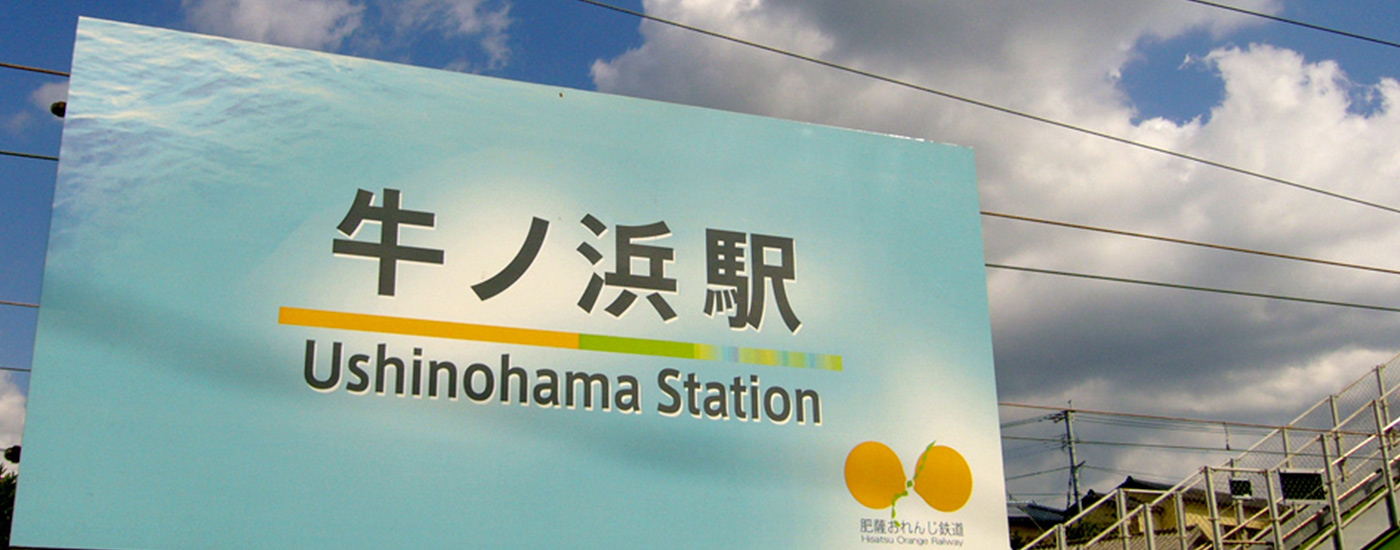
駅という「公共空間」で機能する書体
建築家 川西 康之氏
デンマーク王立芸術アカデミー都市デザイン科招待生として渡欧後、オランダDRFTWD officeやフランス国鉄交通拠点整備研究所(AREP-SNCF)都市設計部などで活躍した建築家の川西康之氏が、2004年に手がけたのは肥薩おれんじ鉄道(八代駅〜川内駅)のロゴタイプとサイン計画でした。
JR鹿児島本線の一部であった熊本県八代と鹿児島県川内を結ぶ路線が第三セクター方式で再出発することになりました。肥薩おれんじ鉄道というみずみずしい名称には、旧国名の「肥後」と「薩摩」の頭文字に加え、沿線で栽培されている柑橘類のイメージが盛り込まれています。川西氏は、精度の高い文字と路線にふさわしいデザインを導入することで、駅という空間や鉄道で移動するという体験に新しい視点を盛り込みたいという思いからロゴタイプだけでなく、統一的なサイン計画を提案しました。
そのために川西氏が選んだのはAXIS Fontでした。風光明媚な自然に囲まれた空間であり、かつミニマムな要素のみで構成された駅舎にはシンプルであたたかみのある書体がふさわしいと直感したのだそうです。
「利用者のためにできることを考えたときに凛として白に映えるAXIS Fontしか考えませんでした。書体としての完成度だけでなく、日本語と英語を併記した時のバランスの良さは抜群ですね。駅名を漢字・ひらがな・アルファベットで同じスペースに配置しても違和感が無い。私は建築家であり、グラフィックデザインを専門的に学んできたわけではないにもかかわらず、完成度の高い文字組を実現できたのはAXIS Fontのおかげだと思っています」
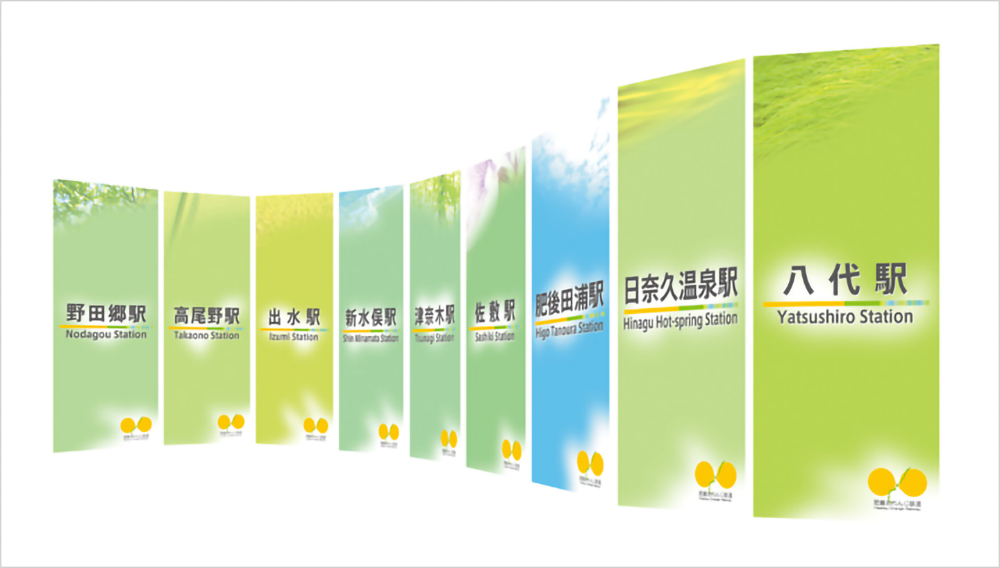
川西氏は土佐くろしお鉄道の主要駅のひとつである中村駅のリノベーションも手がけました。こちらも第三セクター方式を導入し1988年に誕生した路線です。当初はJR中村線を引き継ぐかたちで運行していましたが宿毛線やごめん・なはり線も加わり、現在では高知県の基幹をなす公共交通機関として地域住民や観光客に親しまれています。
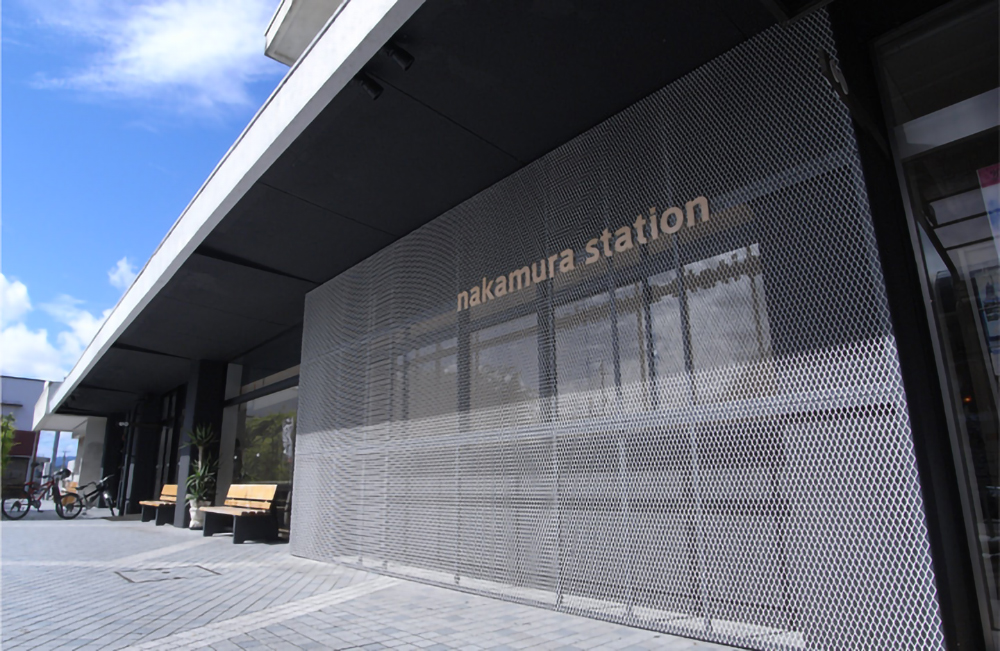
2010年、川西氏が設計した中村駅の新しい駅舎が完成しました。鉄道会社の立場から駅舎の動線を整理して効率的に動ける空間を目指し、また利用者の立場から単なる乗り場ではなく公共空間として機能させることが考慮されています。公共空間としての駅舎には地元の四万十檜をふんだんに使った勉強や読書ができる場所が設けられ、照明を効果的に配置して女性やお年寄りがリラックスできるスペースになっています。その設計は高く評価され、グッドデザイン特別賞 中小企業庁長官賞や日本鉄道賞特別表彰 地方鉄道駅舎リノベーション賞など、受賞歴は10件におよびます。
駅舎ではさまざまな情報が交錯しています。その中でもっとも大切なのは路線図や時刻表、料金表などの鉄道の運行に関わるデータです。川西氏は優先順位の高さを示すために、目線の上に路線図や時刻表を設置し、目線の下には地元企業の広告や行政のお知らせなどを掲示するというルールを設定しました。
「時刻表や料金表でもAXIS Fontを使用して、肥薩おれんじ鉄道のとき以上にAXIS Fontの潜在力を実感しました。特に時刻表の場合、限られたレイアウトスペースで数字をしっかり読ませなきゃいけない。AXIS Fontの場合、厳しい条件下であっても視認性と可読性が高いのです。中村駅では試験的にデジタルサイネージを導入していますが、デジタルデバイスでの使用もまったく問題ありません」
鉄道の根幹を成すのは路線図と時刻表です。運行本数に比例して、AXIS Fontのような書体の重要度も増していくのではないかと川西さんは考えています。CondensedやCompressedのような独自の長体、あるいはAXIS Latin Proに含まれるイタリックなど、豊富なバリエーションを組み合わせることによって、さまざまな見せ方が可能になるからです。
「都市部で顕著ですが、英語のみならず簡体字やハングルを併記する例が急増しています。今後はアジアを見すえた多言語対応の書体が必要になるのかもしれません。今後の開発にも期待しています」